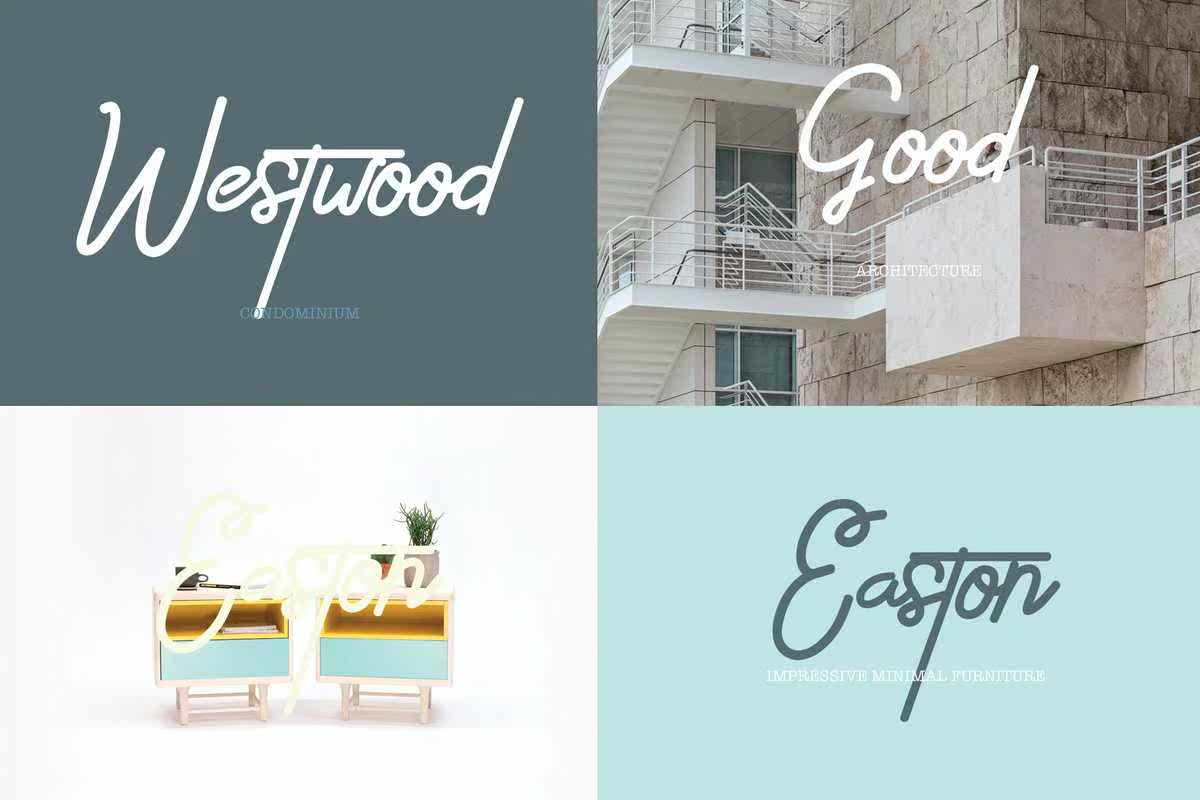
介绍EthonsStyles Amonline和Signatures Types,使用EthonsStyles完成您的完美设计,让您感受到最完美的签名样式。介绍EthonsStyles Amonline和Signatures Types,使用EthonsStyles完成您的完美设计,让您感受到最完美的签名样式。